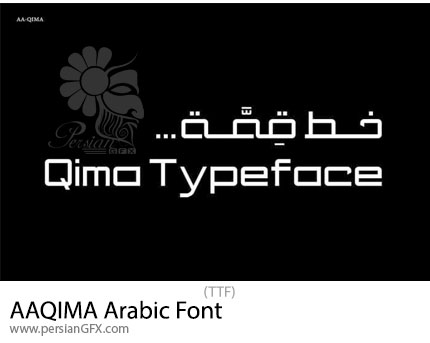
در این بخش شاهد فونت عربی قمـة می باشید که با فرمت TTF بر روی سایت برای دانلود قرار گرفته است. فونت AAQIMA Arabic یک فونت عربی است که برای طراحیهای گرافیکی، تایپوگرافی و محتوای نوشتاری به زبان عربی و فارسی استفاده میشود. این فونت میتواند دارای سبکهای مختلفی مانند کلاسیک، مدرن، خوشنویسی، کوفی یا نسخ باشد که به نیازهای طراحان و کاربران در پروژههای گوناگون پاسخ میدهد. این فونت بهگونهای طراحی شده که حروف عربی و فارسی را با وضوح بالا و ساختاری هماهنگ نمایش دهد. این فونت مناسب برای لوگوها، بنرها، پوسترها، بروشورها، کارت ویزیت و طراحی وب می باشد.